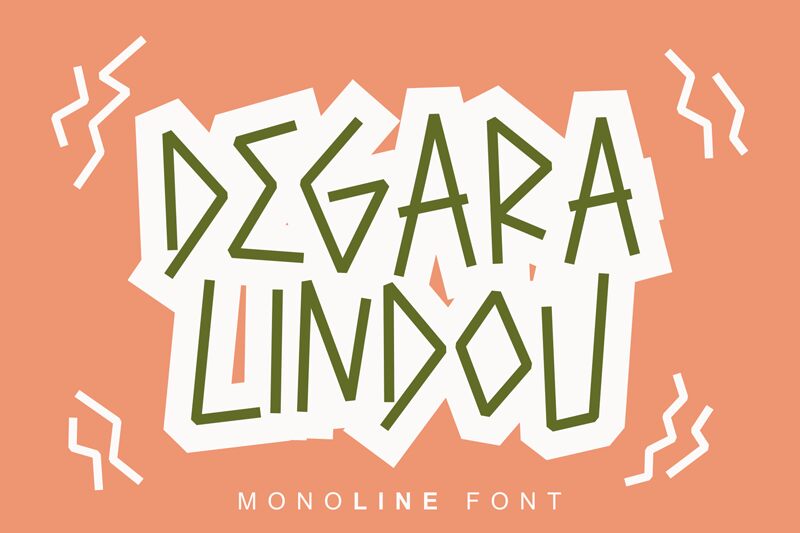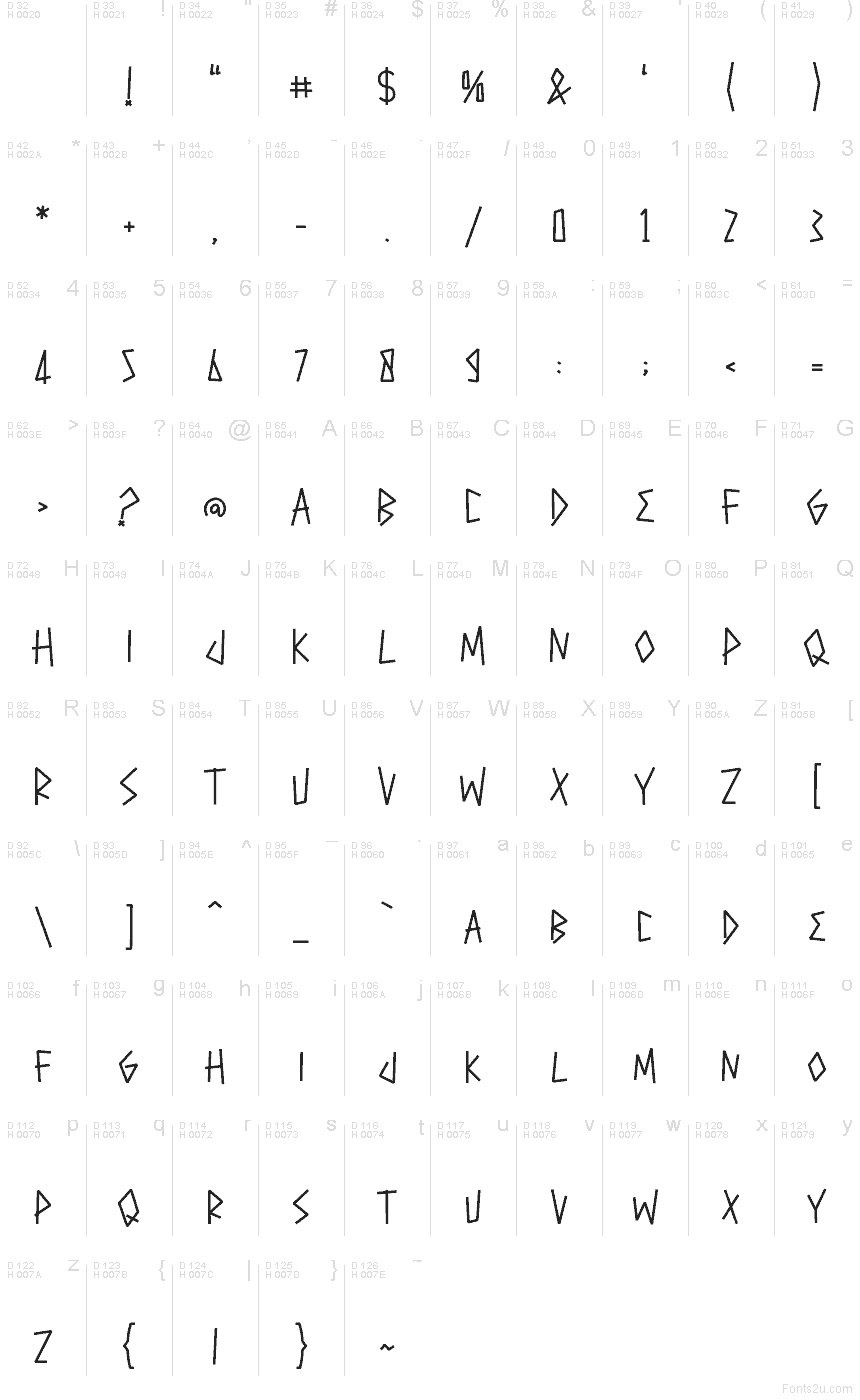
Degara Lindou, do Mabhal Studio, é uma fonte gratuita de letras maiúsculas em estilo grego, com um toque de pedra esculpida e inscrições clássicas. As letras são formadas por diagonais afiadas e formas triangulares abertas, conferindo à fonte um ritmo elegante e artesanal, que remete mais a marcas ancestrais e runas modernas do que a um estilo clássico polido.
É perfeita para títulos de pôsteres, nomes de jogos, branding com temática mítica, flyers de eventos e capas de álbuns onde uma nota marcante e cerimonial ajuda a criar o clima. Como é uma fonte gratuita, ela também funciona muito bem para cartões de título curtos e monogramas, já que as formas pontiagudas e os traços com visual fragmentado mantêm até poucas letras com uma carga gráfica expressiva.